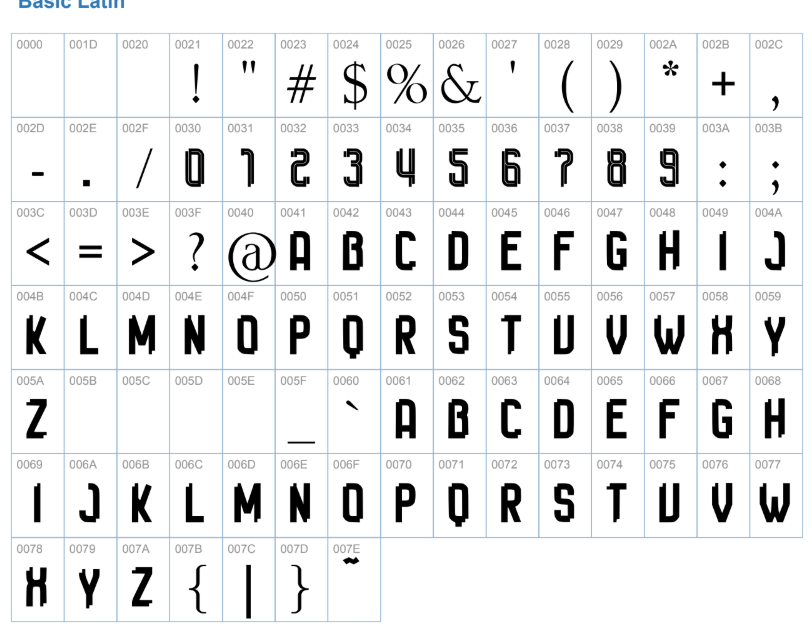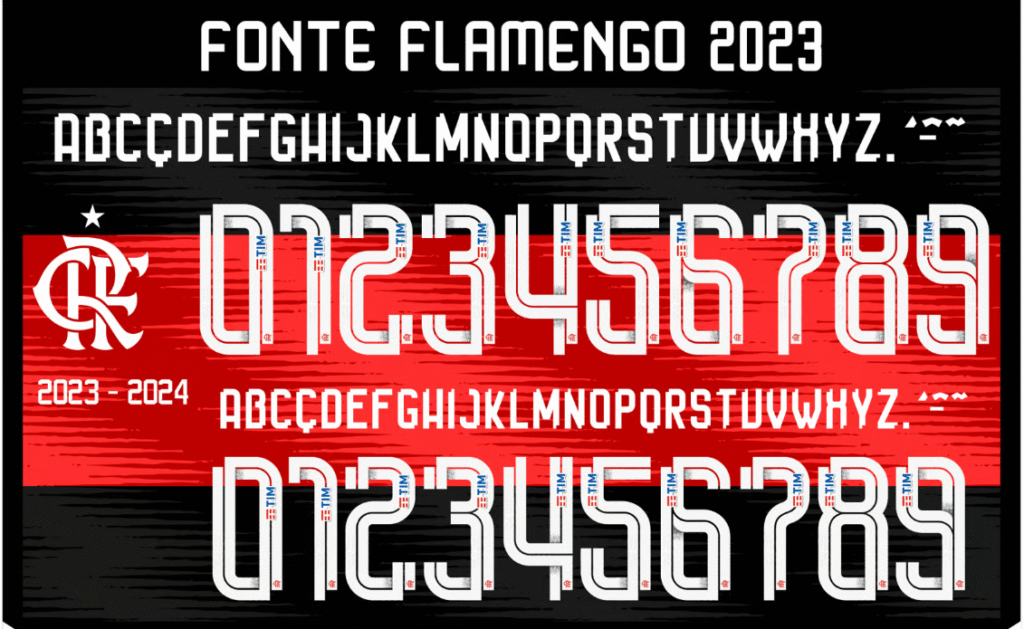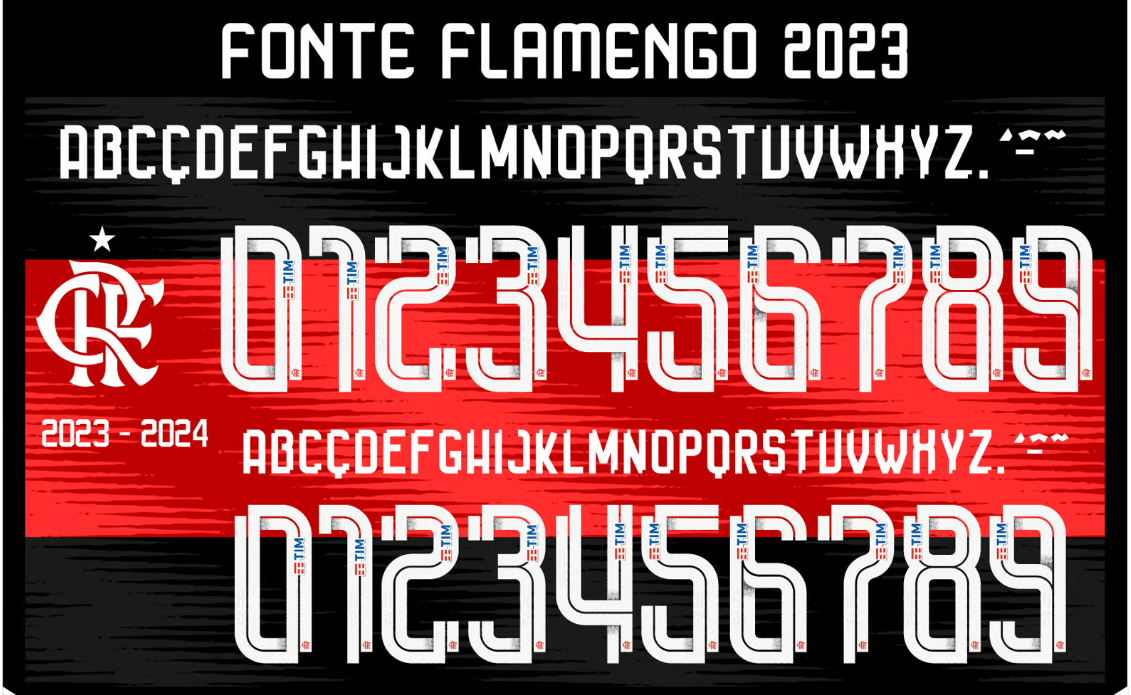
A temporada 2023 marcou mais um capítulo na gloriosa história do Clube de Regatas do Flamengo. E como todo grande time, o Manto Sagrado, assinado pela Adidas, veio acompanhado de uma tipografia que vestiu os craques do Mengão. Mais do que apenas letras e números, essa fonte carrega a energia vibrante da Nação Rubro-Negra.
O Estilo da Fonte Flamengo 2023
A tipografia utilizada pelo Flamengo em 2023 faz parte do template global da Adidas para a temporada (visto também em times como Real Madrid e Manchester United no período). Ela se destaca por um design angular, moderno e extremamente legível.
Com cortes retos e uma leve inclinação, a fonte transmite uma sensação de velocidade e dinamismo, características essenciais do futebol moderno. Ela foi desenhada para ter máximo impacto visual e clareza na TV e no campo, marcando presença nos uniformes 1 (Rubro-Negro), 2 (Branco) e nos kits alternativos daquela temporada.